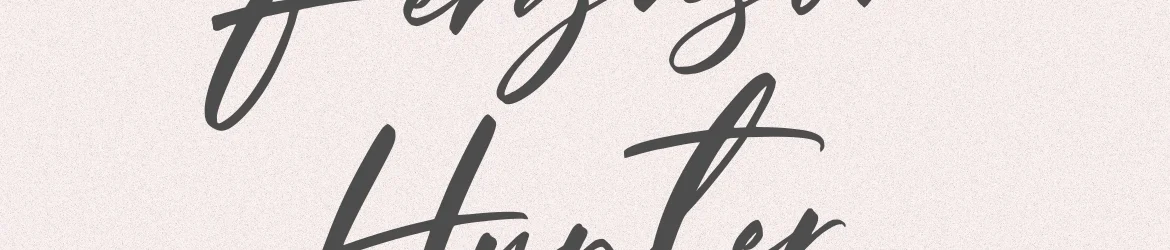
Ferguson Hunter Font – Download Grátis
A Ferguson Hunter é uma deliciosa tipografia script que transmite encanto e leveza com cada caractere. Suas letras tem um toque divertido e dançante, quase como se fossem figuras vivas. Este belo conjunto de caracteres se adequa perfeitamente a qualquer tópico ou estilo gráfico em que seja usado, pois tem o potencial de revitalizar as suas criações. Embora a descrição original esteja baseada em um ambiente digital, imagine Ferguson Hunter como uma fonte que ganha vida ao ser usada no papel. Suas curvas fluidas e formas arredondadas parecem dançar sobre o papel, criando texturas e movimentos sutis que podem adicionar um toque de vivacidade à sua tipografia. Ferguson Hunter não apenas proporciona beleza gráfica, mas também uma sensação de leveza e alegria, tornando-a perfeita para qualquer aplicação em design editorial ou publicitário. Como designer balpirick desenvolveu esta fonte com carinho, cada caractere se destaca como um trabalho de arte único. Ferguson Hunter oferece aos criativos uma maneira elegante de introduzir elementos distintos e divertidos ao seu trabalho gráfico, tornando qualquer projeto mais envolvente e atraente. Com sua versatilidade na criação de texturas e suas capacidades para personalização única, Ferguson Hunter é uma fonte que merece estar em qualquer coleção de fontes elegante e alegre no seu ateliê ou design gráfico.